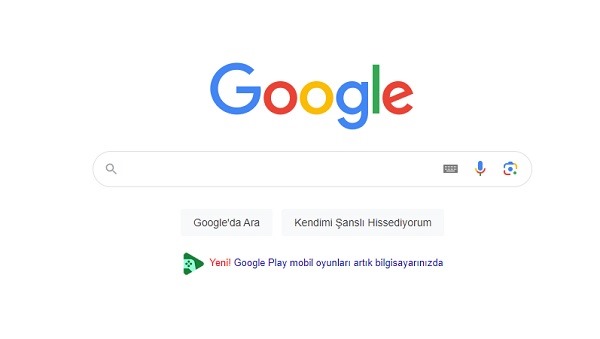
Google.com hangi yazı fontunu kullanıyor ?
Google'ın fonts dünyasına derin imzası vardır. 2010 yılında ücretsiz ve indirilebilir yazı tipleri Google fonts sitesi ile milyarlarca insanın hizmetine sundu.
Bu web sitesi aracılığıyla milyarlaca web sitesi font gömmeden yüzlerce ücretsiz yazı çeşidi kolayca kullanım imkanına erişti.
Google.com hangi yazı fontunu kullanıyor ?
Google.com arama motoru web sitesinde beşten fazla font kullanıyor.Arial, Roboto, Helvetica, Heebo, Google Sans ve diğerleri.
İlk açılış sayfasında ve sorgu sayfalarında genelde Arial fontunu kullanıyor. Arama kutusunun önermesinde iseroboto ve detaylara girincegoogle sans,heebo font ve diğerlerini kullanıyor.
Google font tercihleri sabit değildir. Yıllara, işletim sistemine, mobil kullanıma ve hatta tarayıcılara göre değişmektedir.
Google neden Microsoft Arial yazı fontunu tercih ediyor?
Microsoft Google'ın en büyük rakiplerinden olmasına rağmen aynı zamanda Google en büyük zorunlu partneridir. Arial dünyadaki tüm bilgisayarlarda (MacOs'lar dahil) bulunur. Google Arial Font'u sayesinde hergün yapılan milyarlarca sorgunun yanı sıra birde font yükleme yükünden kurtarmış oluyor. Google'un Arial tercih etmesi sevgisinden değil zorunluluğundandır. Arial bu kadar popüler yapan en temel özellikleri ise, karakter olarak kolay okumması ve Helvetica'nın da ücretsiz sürümü olmasıdır.